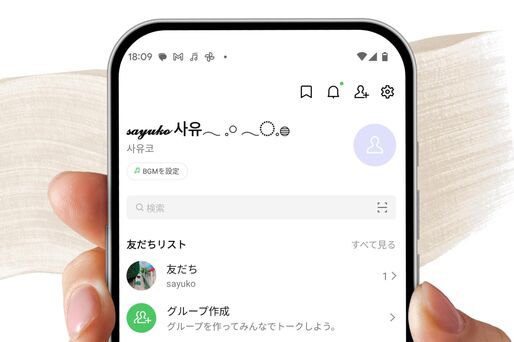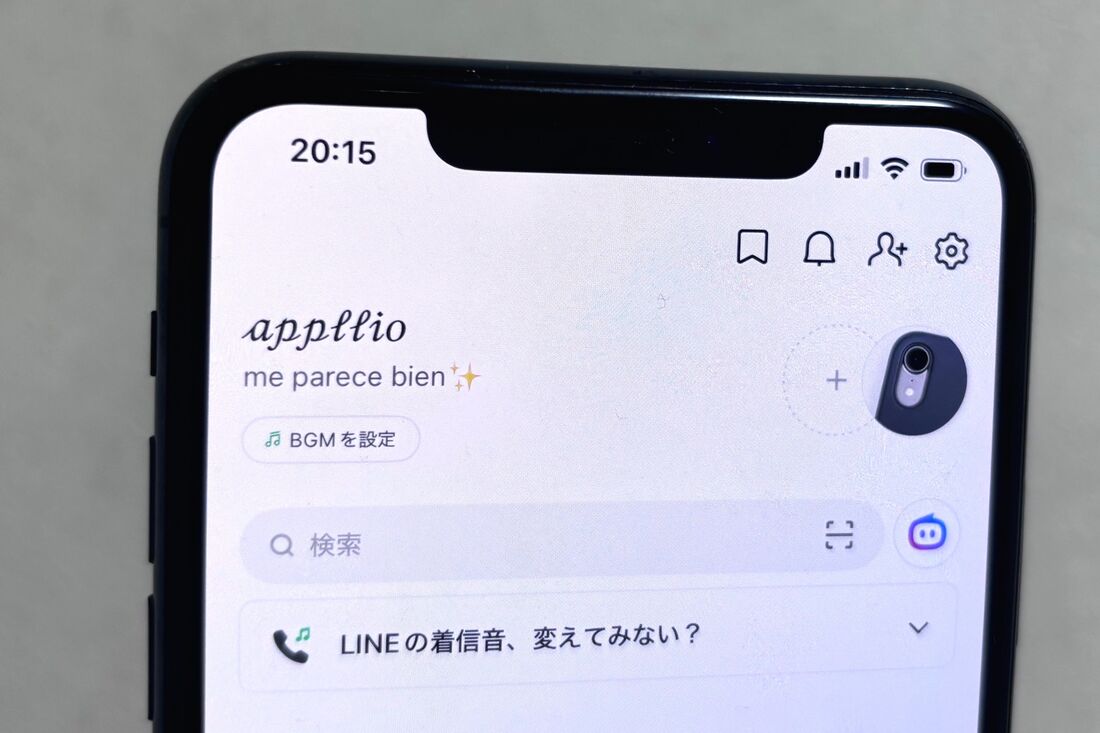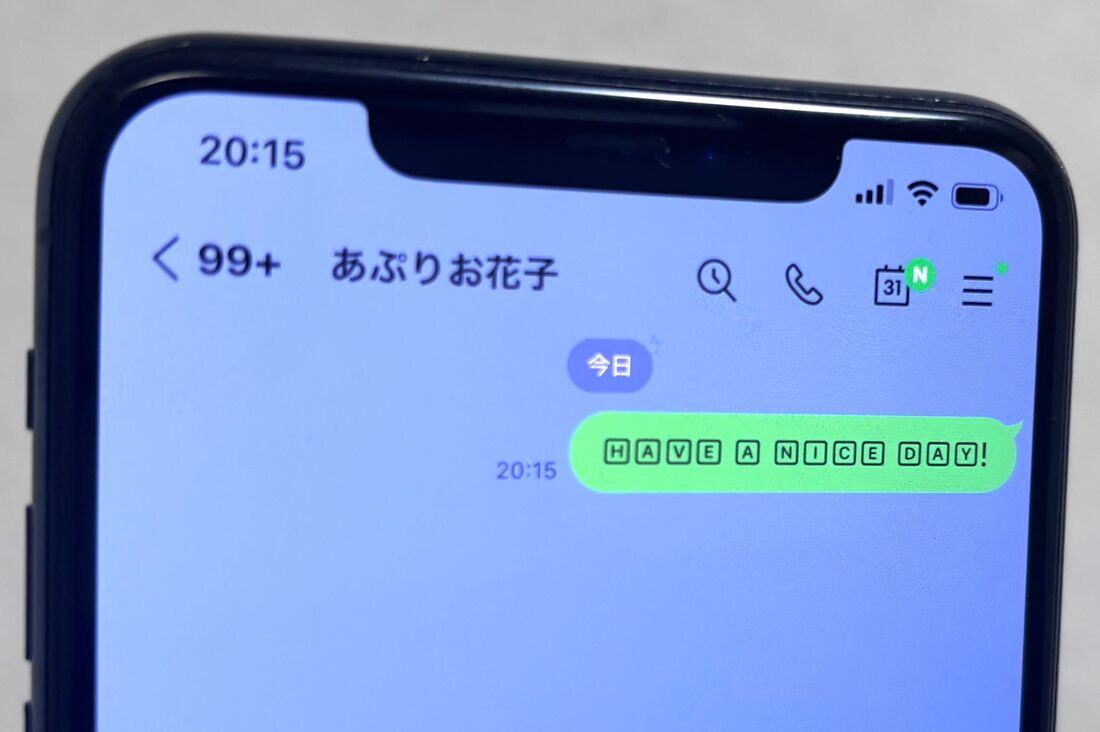
LINEでプロフィール名のフォントが筆記体になっていたり、特殊文字で加工されていたり、少し変わった仕様になっているアカウントを目にすることがあるでしょう。LINEアプリ自体にはこういった文字は用意されておらず、普通に入力してもフォントは変えられません。しかし、専用のアプリやサイトを使えば簡単です。
ただ、フォントや特殊文字のなかには、LINEアプリ上で正常に表示されないものがあるので注意しなければなりません。いわゆる「文字化け」状態になってしまうとアカウントの判別がつかず、友達にも迷惑がかかってしまいます。
そこで本記事では、筆者が実際に検証してiPhone/Androidスマホ両方で文字化けせずに表示できたフォントのうち、おすすめのものをピックアップして紹介。名前の変更手順もざっくり解説しています。
LINEで名前のフォントを変える方法
LINEのアカウント名をおしゃれなフォントに
さっそく、アカウント名のフォントを変更する方法を紹介します。なお、LINEで筆記体や特殊文字が使える(反映される)場所は以下の通り。文字入力ができる場所なら、基本的にどこでもOKです。
- アカウントの名前
- ステータスメッセージ
- トークメッセージ
- LINEグループ名
- LINE VOOM(旧タイムライン)
- LINEノート
メッセージに特殊文字を使えば、いつもとはひと味違ったメッセージを送れます。相手に特別なメッセージを送りたいときに特殊文字を使ってみるのもいいでしょう。
iPhoneの場合:アプリ「フォントくん」を使う
iPhoneユーザーにおすすめなのが、テキストボックスに文字を入力するだけで簡単にフォントを変更できるアプリ「フォントくん」です。
アプリを起動し、フォントを変える
「フォントくん」をダウンロードしたら、上部のテキストボックスに任意の文字を入力しましょう。
すると下に候補が表示されるので、スクロールして好きなフォントを選び、[コピー]ボタンを押します。日本語、英字どちらも対応していますが、英字のほうがたくさんのフォントが揃っています。
LINEアプリを開き名前を変更する
LINEアプリを開き、「ホーム」タブ右上の設定ボタンをタップ。に進んでください。
「名前」の項目をタップしましょう。
文字入力画面が表示されたら、入力欄で[ペースト]を実行。選択したフォントで名前が表示されていればOKです。を押してください。
トーク相手の画面(右)でも特殊フォントの名前が反映されている
「ホームタブ」上部の名前が任意のフォントになっているか確認してみましょう。トーク相手の画面でも、あなたの名前は特殊文字を利用したものに変更されています。
Androidの場合:アプリ「スタイリッシュテキスト」を使う
Androidスマホユーザーには、テキストボックスに文字を入力するだけで簡単にフォントを変更できるアプリ「スタイリッシュテキスト」がおすすめです。
アプリを起動し、フォントを変える
「スタイリッシュテキスト」をダウンロードしたら、まず好きなフォントをスクロールして選択します。
フォントを選択したら上部のテキストボックスに任意の文字を入力。選択中のフォントに変換されているので、[Copy]ボタンを押します。なお、「スタイリッシュテキスト」は英字のみの対応です。
LINEアプリを開いて名前を変更する
LINEアプリを開き、「ホーム」タブ右上の設定ボタンをタップ。続いて[プロフィール]に進みましょう。
「名前」の項目をタップしてください。
文字入力画面が表示されたら、キーボード上部に表示された特殊文字変換後の名前をタップします(端末によっては入力欄でペーストをする)。
選択したフォントで名前が表示されているのを確認し、[保存]を押してください。
「ホーム」タブ上部の名前が任意のフォントになっているか確認してみましょう。
文字化けせずに表示できるおすすめフォント
ここからは、LINEの名前におすすめのフォントを紹介します。筆者が検証して正常に表示された(文字化けしない)フォントのみを取り扱っています(検証端末は末尾記載)。
なお、ここで紹介するすべてのフォントは、いずれも前述したアプリ「フォントくん(iOS版)」「スタイリッシュテキスト(Android版)」で作成したものです。どちらも、どの字体を使用したのか記載しているので、同じアプリを使用する場合の参考にしてください。
筆記体【𝓪𝓫𝓬𝓭𝓮𝓯𝓰】
優美な印象になる筆記体は、もっとも人気のあるフォントのひとつ。ただ、Android版とiOS版で若干見え方が異なります。多くの人がイメージする筆記体は、Android版のほうが近いかもしれません。
iOS版LINEでの見え方
前述したアプリ「フォントくん」の英語フォント4で作成しています。
iPhone(アプリ「フォントくん」)で筆記体を出す方法
英語フォント4のコピーをタップしましょう。
Android版LINEでの見え方
前述したアプリ「スタイリッシュテキスト」の上から5番目の「Script」で作成しています。
Androidスマホ(アプリ「スタイリッシュテキスト」)で筆記体を出す方法
上から5番目の「Script」を選択し文字を入力。コピーをタップします。
白抜き文字【𝕒𝕓𝕔𝕕𝕖𝕗𝕘】
親しみやすいポップなデザインの白抜き文字。可愛らしさと読みやすさを両立しているのがポイントです。
iOS版LINEでの見え方
前述したアプリ「フォントくん」の英語フォント10で作成しています。
iPhone(アプリ「フォントくん」)で白抜き文字を出す方法
英語フォント10のコピーをタップしましょう。
Android版LINEでの見え方
前述したアプリ「スタイリッシュテキスト」の上から2番目の「Doublestruck」で作成しています。
Androidスマホ(アプリ「スタイリッシュテキスト」)で白抜き文字を出す方法
上から2番目の「Doublestruck」を選択し文字を入力。コピーをタップします。
コミック風フォント【ᗩᗷᑕᗪEᖴG】
ポップな印象のフォントは、飽きのこないデザインで、長く使えるでしょう。
iOS版LINEでの見え方
前述したアプリ「フォントくん」の英語フォント14で作成しています。
iPhone(アプリ「フォントくん」)でコミック風文字を出す方法
英語フォント14のコピーをタップしましょう。
Android版LINEでの見え方
前述したアプリ「スタイリッシュテキスト」の上から4番目の「comic」で作成しています。
Androidスマホ(アプリ「スタイリッシュテキスト」)でコミック風文字を出す方法
上から4番目の「comic」を選択し文字を入力。コピーをタップします。
ドイツ花文字【𝖆𝖇𝖈𝖉𝖊𝖋𝖌】
アニメや漫画などのタイトルで使われていそうな、かっこいいイメージのフォントです。
iOS版LINEでの見え方
前述したアプリ「フォントくん」の英語フォント2で作成しています。
iPhone(アプリ「フォントくん」)でドイツ文字を出す方法
英語フォント2のコピーをタップしましょう。
Android版LINEでの見え方
前述したアプリ「スタイリッシュテキスト」の上から13番目の「Golthic」で作成しています。
Androidスマホ(アプリ「スタイリッシュテキスト」)でドイツ文字を出す方法
上から13番目の「Golthic」を選択し文字を入力。コピーをタップします。
四角や丸の囲みフォント【ⓐⓑⓒⓓⓔⓕⓖ】
ぱっと目を引くデザインの囲み文字。友だちリストの一覧でも埋もれず、すぐ目に留まるはずです。
iOS版LINEでの見え方
前述したアプリ「フォントくん」の英語フォント24で作成しています。
iPhone(アプリ「フォントくん」)で囲み文字を出す方法
英語フォント24のコピーをタップしましょう。
Android版LINEでの見え方
前述したアプリ「スタイリッシュテキスト」の上から18番目の「BOXES」で作成しています。
Androidスマホ(アプリ「スタイリッシュテキスト」)で囲み文字を出す方法
上から18番目の「BOXES」を選択し文字を入力。コピーをタップします。
スマイルマーク付フォント【ă̈b̆̈c̆̈d̆̈ĕ̈f̆̈ğ̈】
文字の上にニコちゃんマーク(スマイルマーク)がくっついた、可愛らしいフォントです。
iOS版LINEでの見え方
前述したアプリ「フォントくん」の英語フォント59で作成しています。
iPhone(アプリ「フォントくん」)でスマイルマーク付フォントを出す方法
英語フォント59のコピーをタップしましょう。
Android版LINEでの見え方
前述したアプリ「スタイリッシュテキスト」の上から39番目の「Smile」で作成しています。
Androidスマホ(アプリ「スタイリッシュテキスト」)でスマイルマーク付フォントを出す方法
上から39番目の「Smile」を選択し文字を入力。コピーをタップします。
文字化けせずに表示できるおすすめの特殊文字
フォントを変えるだけでなく、特殊文字(絵文字)を使うのもおすすめです。主張しすぎない控えめでシンプルなデザインのものばかりなので、名前に添えてあっても悪目立ちしません。
ここでは、特殊文字の中でもアカウント名に使いやすいものをピックアップ。文字化けせず表示されたものを厳選しているので、そのままコピーして利用してみてください。
花・星・リボン【𖤣𖥧𖥣𖡡𖥧𖤣 𖥸 𖤐˒˒ ◌𓈒𓐍 𓈒】
コミック風フォントとリボンの組み合わせ
まずは定番のハートや花、星マークなどをご紹介。使い勝手がよく、どんなフォントとの相性もよさそうです。
花・植物【 ❉ ❊ ❋ ✻ ✼ ✽ ✾ ✿ ❀ ❁ 𖤣𖥧𖥣𖡡𖥧𖤣 𓍯 ✲ 𖠰 𖥍 𖥸 𖦥 𖦞 𖢇 𖧡 𖣔 ꕤ ꕥ 】
星【 ✩ ✪ ✬ ✭ ✮ ✯ ✰ ✦ ✧ 𖤐˒˒ 】
リボン【୨୧ ˖* ⋈ ⑅ 】
水玉【 𓈒 𓏸 𓐍 𓂃 𓈒𓏸 𓂃◌𓈒𓐍 𓈒】
文房具・食べ物【𓌉◯𓇋 ✎𓈒𓂂𓏸 ✎𓂃𓎩 】
筆記体フォントと文房具の組み合わせ
文房具や食べ物の特殊文字は、名前の末尾や頭に添えるだけで、大人かわいい印象になります。自分の趣味や職業をアピールしたい人にもおすすめです。
文房具【 ✂︎ ✐☡ ✑ ✎ܚ ᝰ✍︎ ꙳⋆ ✎𓂃 ✎𓈒𓂂𓏸 ✎೯ ✎✐ 】
食べ物【𓎩 𓌉𓇋 𓌉◯𓇋 𓂑 𓌈 𓂅𓎩 𐩢𐩺】
生き物【𓃰 𓃱 𓆈 𓆏 𓃙 】
LINE公式アカウント「LINE韓国語通訳」を友だちに追加する
LINEの「ホーム」タブで、検索窓をタップし「韓国語」と検索してください。LINE公式アカウント「LINE韓国語通訳」が出てくるので、友だち追加ボタンをタップしましょう。
LINE公式アカウント「LINE韓国語通訳」でトークに名前や言葉を送信する
「LINE韓国語通訳」とのトーク画面で、画面下の[文字を入力]をタップ。普段メッセージを送るのと同じように、好きな文字を入力して送信します。すると、すぐにハングル変換されたメッセージが送り返されてきます。
ハングルに変換された文字をコピーする
トーク画面で、ハングル変換されたメッセージ部分を長押しして[コピー]をタップしましょう。
名前やステメ部分にペーストする
あとはLINEのプロフィール(「ホーム」タブ→設定→[プロフィール])を開き、名前やステータスメッセージ部分にハングルをペーストすれば完了です。
ステータスメッセージ(ステメ)にハングルが設定できました。